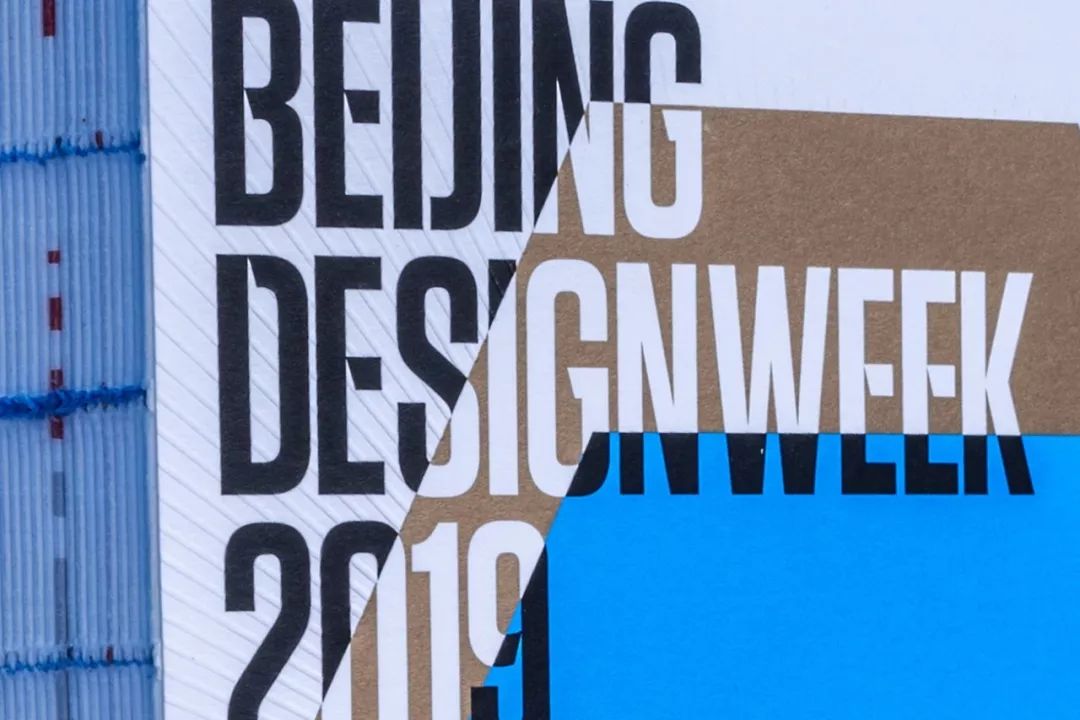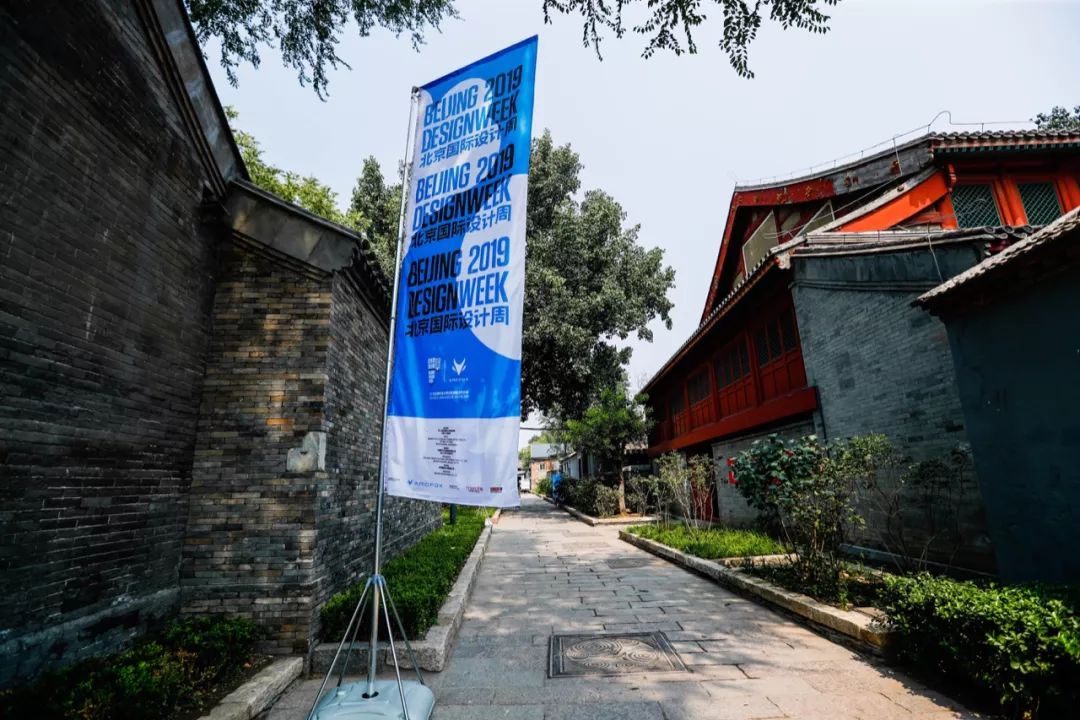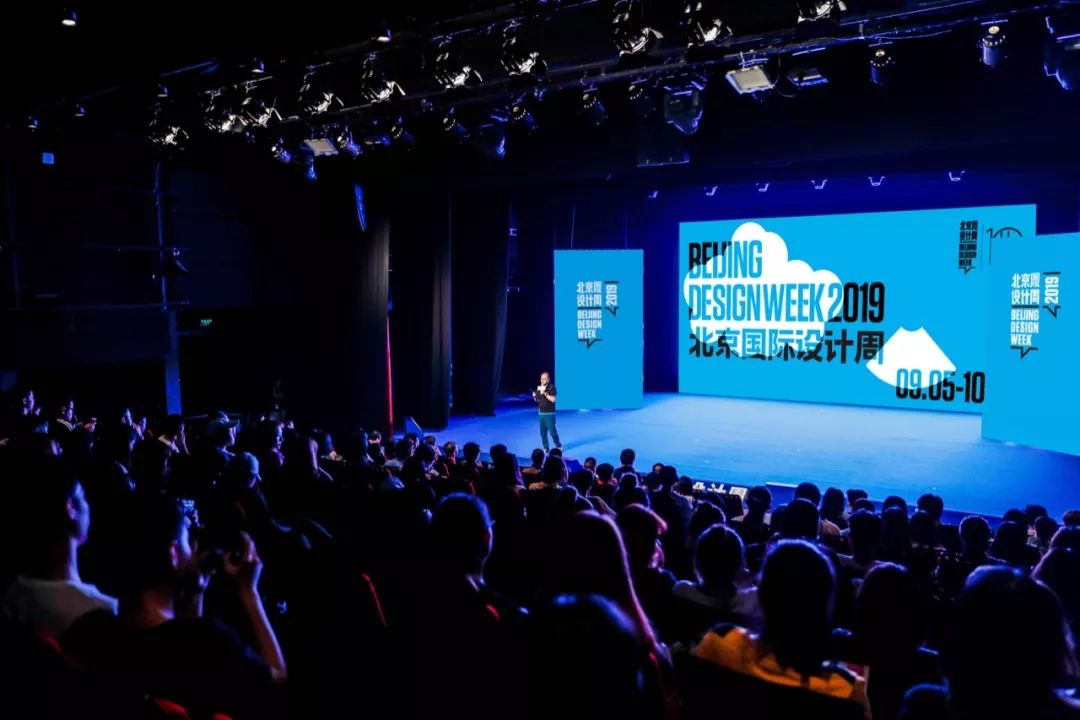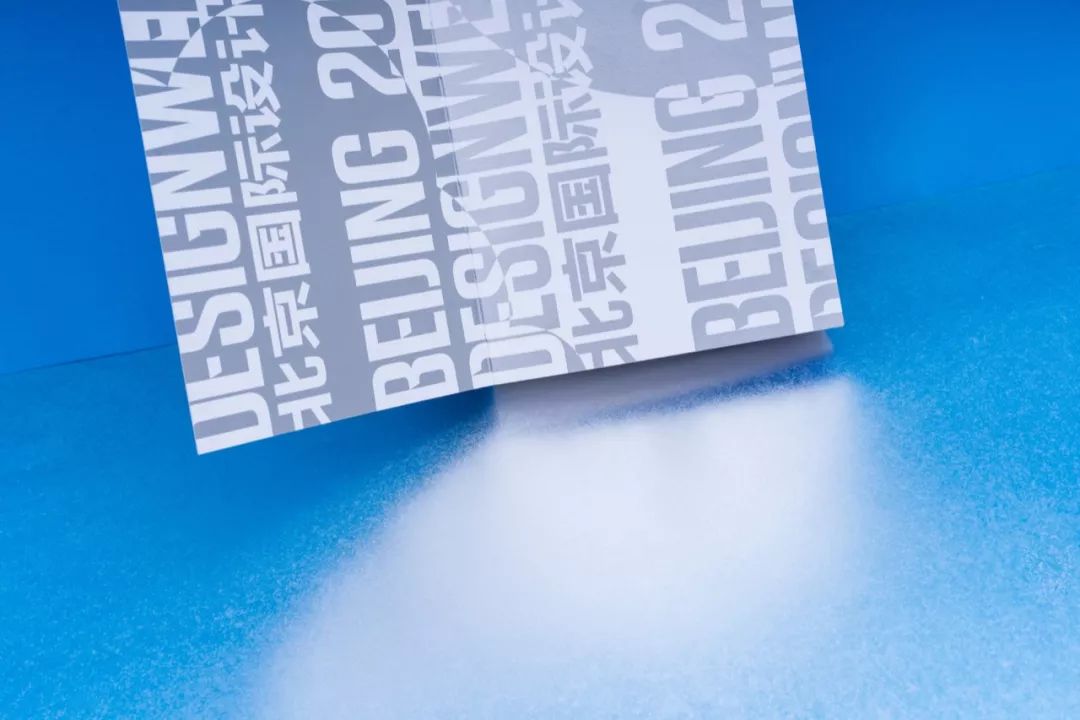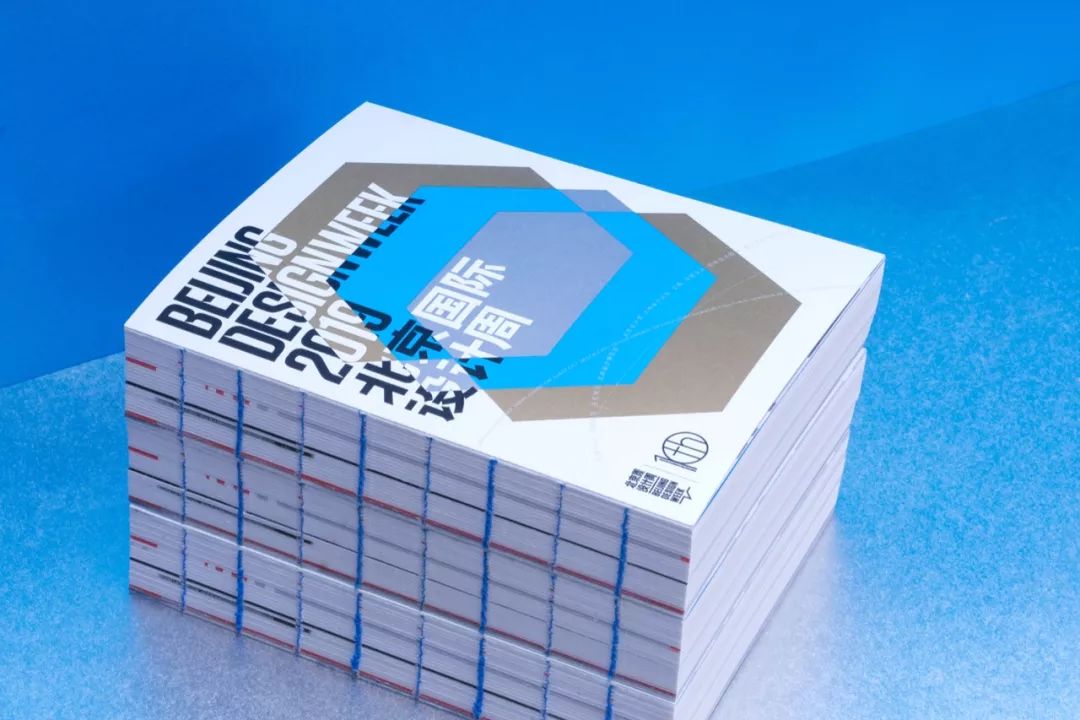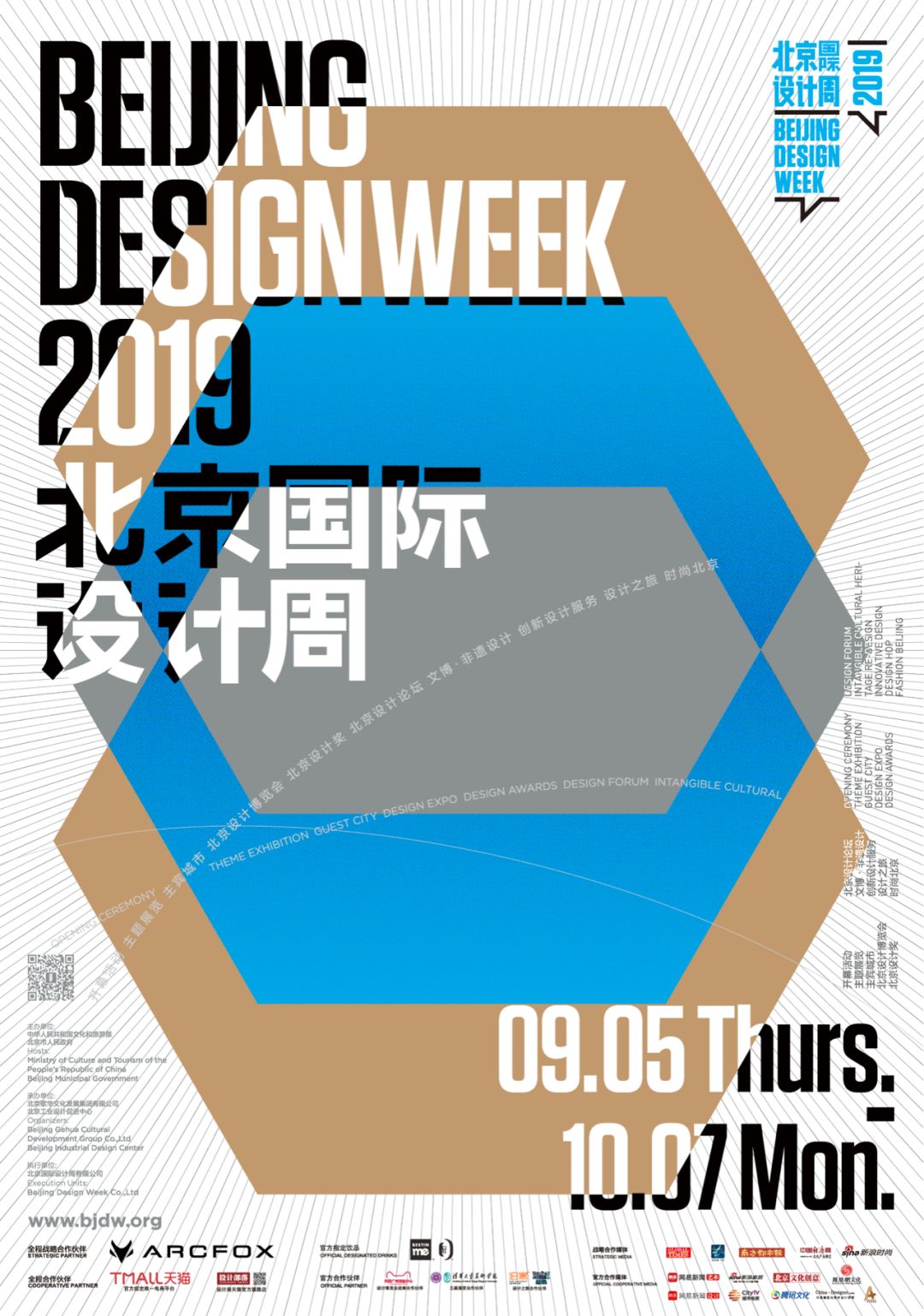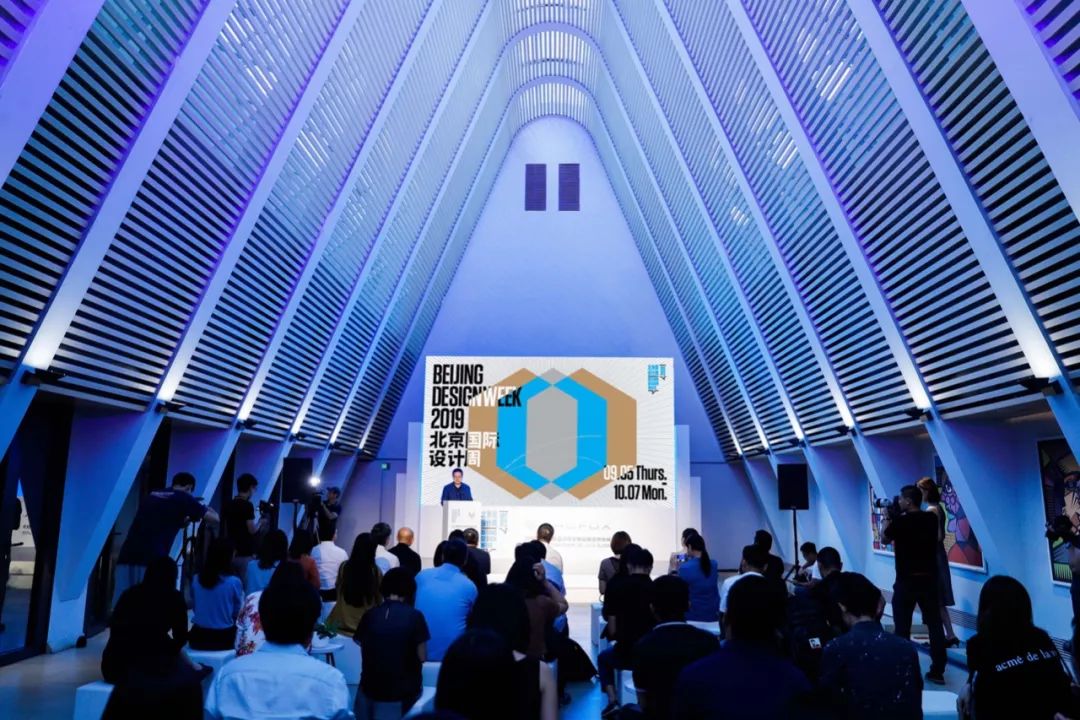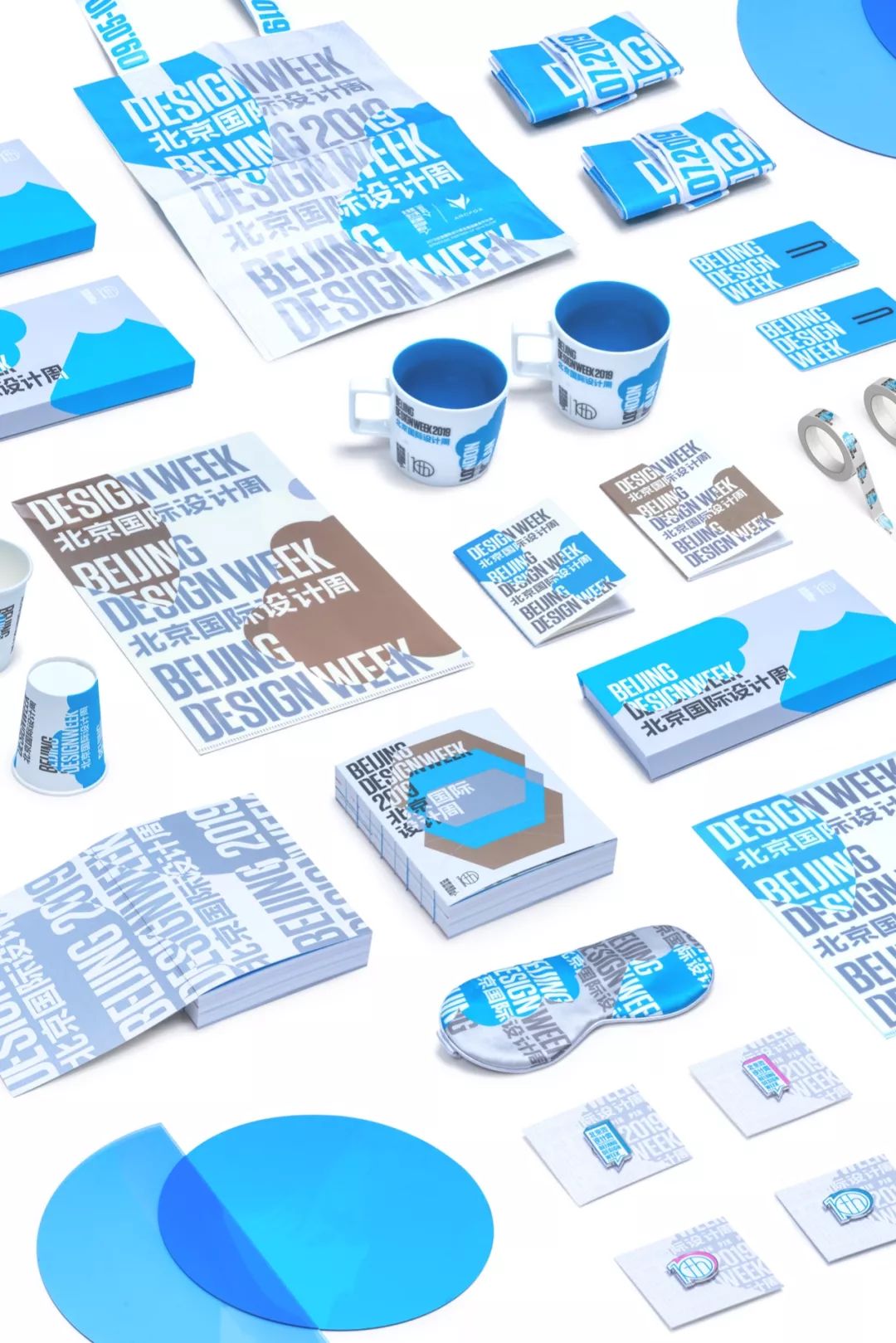
去未知处探险 ,2019北京国际设计周主视觉设计
北京国际设计周主视觉设计
站在21世纪的第二个十年,我们迎来了5G、人工智能、物联网等应用前景广阔的新技术。艺术、设计,科学、大数据……在未来,原本平行的领域,会结合激荡出更多元的表现与互动的可能性,所有未知的探索也都会更具时代性。历史探索带来人类的无限可能,创新驱动经济发展也成为共识,而以设计来策动各个行业发展是北京国际设计周在第一个十年带来的全新主题。科学、技术、艺术等不同领域的融合在当下为不同产业带来合作机遇,就好比建筑师槙文彦对于现代主义的比喻,现代主义已经不再是船,而是一片汪洋大海,大家被放逐于大海之上,不再是朋友也不再是对手。其中的一个浪潮便是同理心,更是在瞬息万变中建立的全球艺术。
视觉现场展示
2019年北京国际设计周视觉由设计师Will温双斌带领团队完成,创作理念及设计元素围绕设计周主题“产业策动”,并以设计周十年的年度主基调为主要设计元素来源,还从本届设计周的设计使命中提取出核心价值,比如设计驱动贸易繁荣、设计赋能城市创新、优秀中华传统文化的产业化创新等方面作为主要视觉语言。
十种元素展示
“十”在中国传统文化的语境下是完美、完整的寓意,当下,人们更愿意把“轮回”或者“回潮”等概念赋予这个数字。比如现在一直被津津乐道的80年代风格,注重设计的装饰性、个性化及人文思想,放弃了无彩色和功能主义。
在十年为一秩的时间节点之上,设计团队除了对概念、文化元素的提取,十个最具代表性的图形元素也是对设计周十年的致敬。图形既传承了中国文化中对“十”的完美、圆融、和谐等概念的阐释,也从21世纪文化巨变背景下提取“十”的多样性、复古回潮、打破因袭等新兴文化语言,设计了十个不同图形作为主视觉元素,分别代表了设计周十个不同的版块。
2019北京国际设计周项目最大的挑战在于:如何在具有十年历史的北京国际设计周的视觉基因上有更新鲜的设计!团队小伙伴们因此丰富了原本独有的设计周蓝,添加了有时代语汇的金色、银色、黑白、荧光粉、荧光绿、荧光粉、藕粉色等色彩,使得颜色运用更灵活多变,视觉效果更加丰富。
突“破”视觉习惯,也成为了设计中最需要解决的挑战。英文部分沿用了Tungsten字体、中文在方正兰亭大黑的基础上做了调整,“三角形”作为“破”的元素,给每个文字凿了窗口,顿生锋利的气息,沉稳设计中包含了细节趣味。
2019北京国际设计周官方海报
主视觉应用
2019北京国际设计周官方会刊
十个元素在会刊运用中出现,它们分别代表了2019年北京国际设计周的十个板块,也呼应了设计周的十年。章节页面也运用了不同的色彩,略带抽象的图形,激活了画面,它们跳跃叠加在一起,贯穿了整本会刊。
封面的印刷工艺上,放射线使用起鼓工艺,给读者惊喜的触感。章节页面配色系统呼应了10个板块的色彩分割,读者可以很容易翻找到相应的内容,提高了阅读的便利性。
在视觉延展的部分中,十个元素开始发挥作用,依旧使用“切割”手法,图形与文字的叠加处做了异色处理,使简单的颜色、文字构图产生出更多变化的可能性。
袋子的部分,在设计上我们选用了延展视觉部分的元素+主视觉海报的放射性元素,大面积的文字,增强了主体内容的传播性。肩带的内容09.05-10.07.2019是北京国际设计周的活动时间,色彩上使用设计周蓝和银色,使纸袋看起来轻盈,也便于日常的使用。
系列笔记本使用了荧光粉、荧光黄、设计周蓝、金色共同组合4册一装的笔记本套装,多彩活泼的配色,使用感受更加轻松。
10周年纪念眼罩
冰箱贴以组合套装形式出现,图形元素挑选了六边形、扇形、10周年纪念组合logo、设计周对话框等元素,突出俏皮感,强化了使用场景。
磁铁徽章
北京国际设计周10周年主宾城市马克杯
论坛现场
创意设计